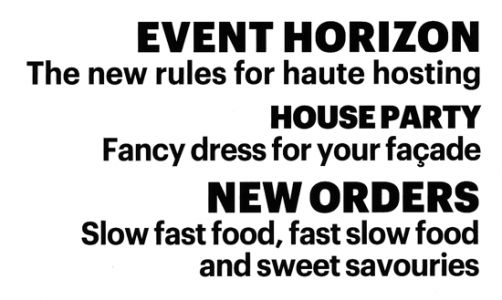
Neue Grotesk im Magazin Wallpaper* gesucht.
suche die neue Grotest, die im Magazin Wallpaper die Amplitude als Display und Textfont ersetzt hat.
die info läßt sich übrigens auch problemlos aus jedem
zweiten pdf auf der wallpaper-website auslesen ...
dort heisst die typo plakat narrow und wird zusammen
mit der lexicon verwendet.
@ Christoph: "Gibt es davon auch digitale Versionen, konnte bei den üblichen Verdächtigen nichts finden?"
Hatte mir eigentlich für ein neues Projekt die Gotham ausgeguckt (mit Schriften von H&FJ hatte ich bisher gern gearbeitet), dann aber die Wallpaper in die Finger bekommen...
...nun bin ich etwas verunsichert.
Leider kommt die Plakat frühestens April 2008 in den freien Verkauf.
Die Flama gefällt mir, ist aber für meinen Zweck zu technisch. Die DIN hatte ich Vorfeld schon getestet und ausgeschlossen.
Die Texte (Jahresbericht, Magazin & Co), in diesem Projekt laufen in der Compatil (Text & Fact)... Die ersten Entwürfe hatte ich mit der Verlag gemacht, die passte aber nicht wirklich – war irgendwie zu weich. Ansonsten kann ich die Verlag nur empfehlen, gute Alternative zu Futura, Neutra & Co.
Bei der Plakat hatte mir die Einordnung irgendwo zwischen Futura und Helvetica zugesagt – schöne Mischung, aber eben leider nicht erhältlich.